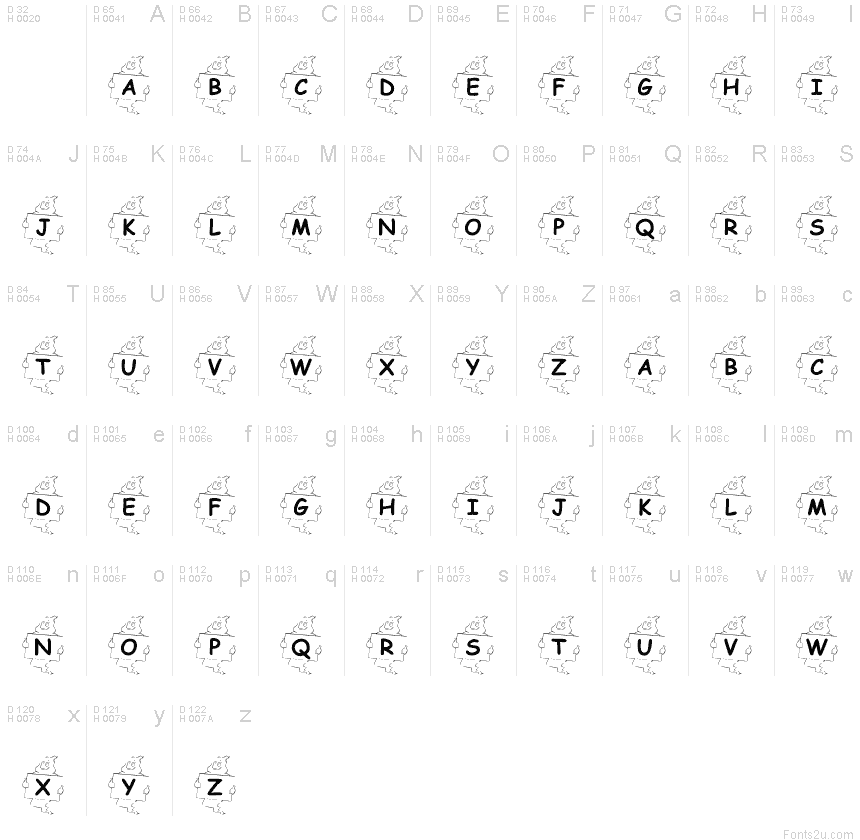
KR Ghostly Message da Katsfunfonts é uma fonte decorativa gratuita para o Halloween que transforma cada letra em um fantasminha amigável. Cada caractere repousa sobre um espectro trêmulo desenhado à mão segurando uma placa, com letras suaves e arredondadas que parecem mais doces do que assustadoras. Os contornos finos e o estilo de esboço, aliados aos rostos alegres, dão a toda a fonte um charme leve e desenhado à mão que permanece legível mesmo em tamanhos maiores.
Com KR Ghostly Message, você pode criar convites de Halloween para crianças, atividades escolares, murais, etiquetas para doces, adesivos e posts divertidos para redes sociais. Esta fonte gratuita brilha quando os fantasmas aparecem grandes e em destaque; combine-a com uma fonte sem serifa limpa para detalhes menores, para que as letras ilustradas continuem sendo a estrela do show.